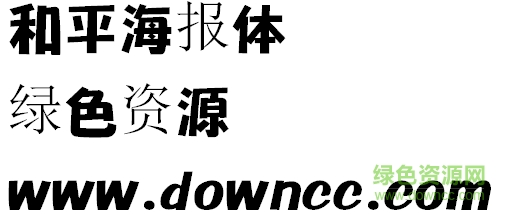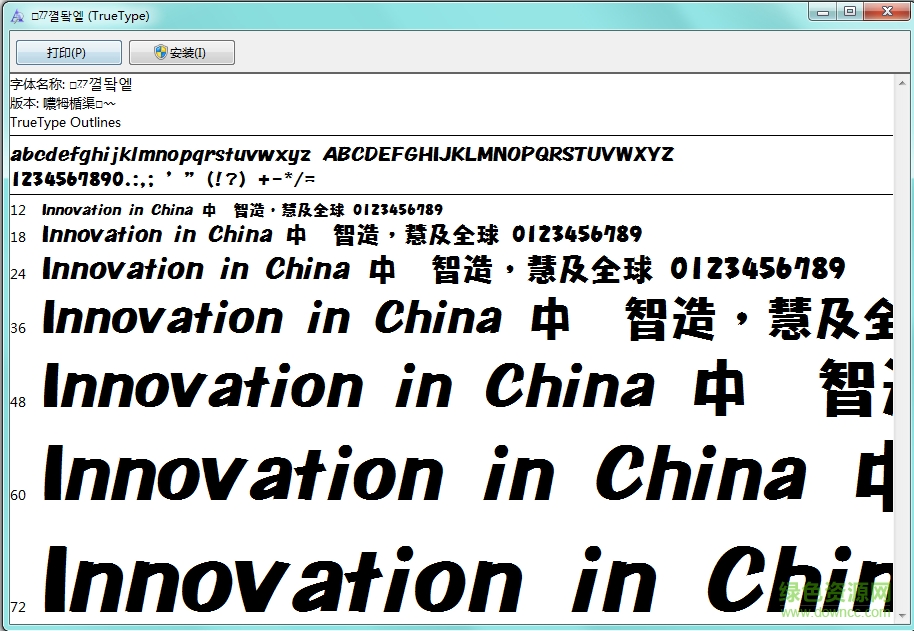
和平海報字體
和平海報體是一款有著獨特造型的海報字體,造型微斜經(jīng)過加粗后,有著顯眼的外觀和悅目的觀賞體驗,支持繁體輸入,需要的朋友來綠色資源網(wǎng)即可免費下載!
和平海報體,支持繁簡輸入,如部分簡體字無法見識,需手工轉(zhuǎn)換成繁體。字形經(jīng)過加粗處理更加顯目,適合于廣告創(chuàng)意、平面設計、海報策劃等場景。